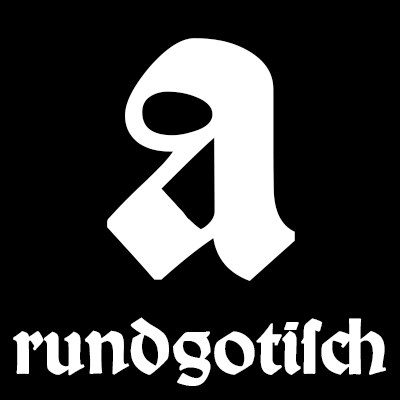
- 1930
- Gebrochene Schrift
Die Wallau soll von einem Blatt einer italienischen Missale aus dem 14. Jahrhundert inspiriert sein, das in der Werkstatt Rudolf Kochs hing. Die Erstellung dieser rundgotischen Schrift zog sich mehrere Jahre hin. 1930 erschien sie bei Gebr. Klingspor. Bis 1935 wurde die Schrift auf vier Schnitte ausgebaut.
Benannt ist die Schrift nach Heinrich Wallau, einem Buchdrucker aus Mainz. Er schrieb 1885: »Der Zug des Schreibrohres ist der aller Schriftform innewohnende und wesentlich mitbestimmende Faktor. Seine eigentliche Ausdrucksweise auf die Druckschrift auszudehnen muß schon im Hinblick auf die Tatsache gerechtfertigt erscheinen, daß damit für die Schrift ein fester Standpunkt eingenommen wird.« Im Sinne dieser Maxime wirkt die Wallau, wie auch viele andere Schriften Kochs, wie handgeschrieben.
Digitalisierungen in guter Qualität gibt es von Delbanco und Gerhard Helzl.